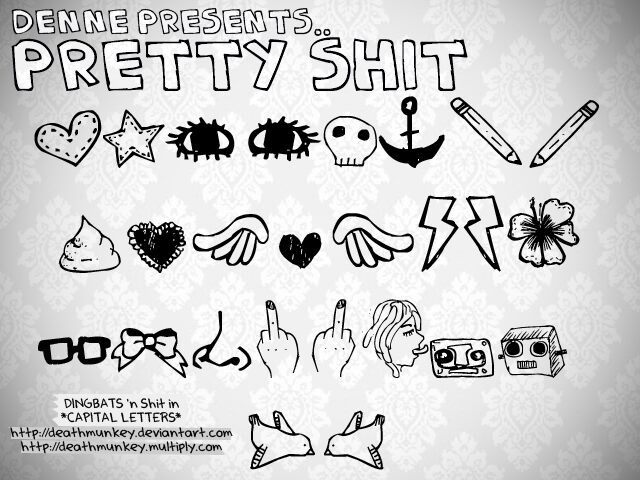
Denne, entworfen von Denise Bentulan, ist eine kostenlose Dingbat-Schrift, die auf einem kräftigen, handgezeichneten Hibiskus-Motiv basiert. Unregelmäßige Linien, kantige Blütenblätter und dichte, aus der Mitte strahlende Striche verleihen der Grafik einen charmanten, fast cartoonartigen Look anstelle eines sterilen, botanischen Stils.
Diese kostenlose Schrift eignet sich perfekt für tropische Event-Poster, Zine-Cover, Surf-Grafiken, Verpackungsdetails und handgemachtes Branding. Die kompakte Blumenform funktioniert auch hervorragend als Schmuckelement für Titel oder als auffällige Seitenmarkierung, besonders dort, wo der raue Strichcharakter zur Geltung kommen soll.